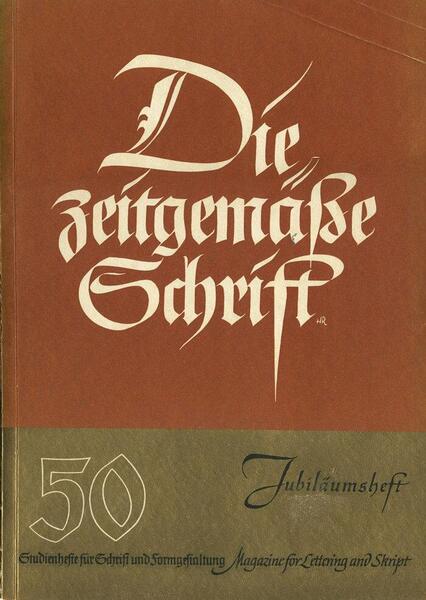
Das Unternehmen Heintze & Blanckertz wurde im Jahr 1849 von Rudolf Heintze und Heinrich Blanckertz gegründet und machte sich mit der Entwicklung und Herstellung von Schreibfedern schnell einen Namen. Da es bis in die dreißiger Jahre des 20. Jahrhunderts keine Füllfederhalter oder Kugelschreiber gab, entwickelte sich die Firma rasant. Heinrichs Sohn Rudolf Blanckertz führte die Geschäfte später fort und eröffnete 1926 ein Schriftmuseum in Berlin.
Begleitend zur Federproduktion und den Museumsaktivitäten wurde ab 1928 die Zeitschrift »Die zeitgemäße Schrift« herausgebracht. Sie gilt als eine der ersten Designzeitschriften. Sie war ein indirekter Werbeträger für die eigenen Produkte und Angebote (z.B. die Ausstellungen des Museums), aber informierte vornehmlich in Form von Fachartikeln über die eigenen Angeboten nahestehende Themen, insbesondere die kalligrafische Schriftgestaltung. So wurden Künstler wie Heinrichsen, Koch, Hupp, Johnston etc. vorgestellt und die Schriftgeschichte und stilistische Entwicklungen beleuchtet. Während der Zeit des Nationalsozialismus positionierte sich das Heft klar auf Seite der Traditionalisten und warb für die gebrochenen Schriften als »deutsche Volksschrift«.
Die Zeitschrift wurde 1943 mit der Ausgabe 64 kriegsbedingt eingestellt.